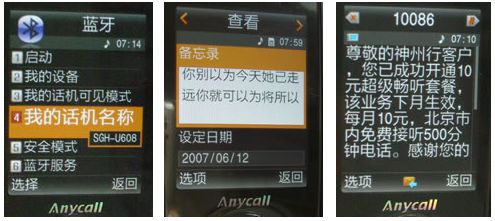
方正字体嵌入解决方案
方案介绍
随着现代电子与信息技术的不断发展,信息处理产品的种类越来越多。常 见的涉及信息处理的软件产品和嵌入式系统包括:桌面操作系统(Windows、Mac、Linux、Unix等)、具有文字处理功能的软件(Office、CAD、OA等)、打印输出设备(Printer) 、手机(Mobile Phone)、电子书(eBook)、电子字典、机顶盒(Set top box)、导航仪(Navigator、GPS)、数字电视系统(Digital TV)、车载娱乐终端(Car dvd entertainment system)、医疗系统、工业控制系统等。为了便于人机交流,多数信息处理产品都配有显示装置。文字是显示装置上最重要的信息!方正作为最资深的中文字体专 业开发商,长期为信息处理软件及嵌入式系统提供完整的用字解决方案。针对液晶显示屏的显示特点,方正公司专门设计并开发了更加易于阅读、清晰美观、实用性强的字体。同 时,为尽可能少的占用嵌入式系统的存储空间,方正还专门开发了采用笔划压缩技术的字库产品,可节约超过75%的存储空间。
以下是方正字体的相关资料,供信息处理软件及嵌入式系统技术开发者参考:
一、方正支持的常用编码标准
1、GB编码:中国大陆使用的国家标准,其中GB2312-80、GBK、GB18030- 2000比较常用;
2、BIG5编码:港台及海外华人常用的标准。香港地区由于方言用字较多,而且与内地交流较多,所以在BIG5的基础上又增补的几千个“香港字”,简称 :HKSCS。目前最新的版本是HKSCS-2008。定义字符5009字;
3、JIS编码:日本国的国家标准;
4、KSC编码:韩国的国家标准;
5、欧洲语系编码:可以支持:英语English、德语Germany、波兰Polish、匈牙利Hungarian、葡萄牙Portuguese、捷克Czech、意大利Italian、西班牙 Spanish、法语French、荷兰Dutch、芬兰Finnish、希腊Greek、土耳其Turkish、瑞典Swedish、俄文Russian等多国语系;
6、Unicode编码:Unicode是国际组织制定的可以容纳世界上所有文字和符号的字符编码方案。方正公司提供的字库完全支持Unicode编码方式;
7、其它语系编码:方正公司可以根据用户的需求定制提供支持其它语系编码方式的字库。
二、常用的字库格式
目前,字库常用的种类有点阵字库和TTF字库(所谓“矢量字库”)。
点阵字库(Bitmap font、Dot matrix font)适合精度很低的显示设备。常用的格式主要有“DAT”、“BDF”、“FNT”、“PCF”、“BMP”等。
TTF字库(TrueType)适合较高精度的显示设备。由于TTF字库是通用、标准的字库。因此,只要是带有TTF解释器的系统都可以直接使用。如:Windows 系统、Symbian系统、Android系统、Unix系统及其它Liunx系统等。
三、推荐的字体种类(应用效果图)
点阵字库:方正公司可以提供支持GB(中国大陆标准)、JIS(日本标准)、KSC(韩国标准)和欧洲语系标准的各种尺寸点阵字库。
TTF字库:针对屏幕显示的特殊性,方正公司专门开发了采用标准TTF压缩格式的黑体、宋体风格的字体。
以下是方正推荐的屏幕用黑体、楷体和宋体的普通字体的对比样例
方正屏幕用黑体与普通黑体的对比效果
注:带有*的为方正屏幕黑体
方正屏幕用宋体与普通宋体的对比效果
注:带有*的为方正屏幕宋体
方正屏幕用楷体与普通楷体的对比效果
注:带有*的为方正屏幕楷体
五、常见问题:
3、关于Unicode的问题
许多主权国家都制定了本国的编码标准,这些编码也叫地区编码,如GB(中国标准)、BIG5(港台标准)、JIS(日本标准) 。Unicode是国家上通用而统一的编码体系。任何一个地区编码与Unicode编码之间都有一一对应的关系。字体厂商提供的字库通常以Unicode编码方式提供,字符集支持地区编码。 地区编码与Unicode编码之间的转换由操作系统完成。
4、使用Unicode编码字库是否可以同时满足中、日、韩市场?
Unicode编码字库可以同时支持中、日、韩三地,但由于文化的差异,许多同一个编码的汉字的写法却不一样。因此,完美的 解决方案是分别使用三个字库支持中、日、韩三国市场的产品。以下是中国大陆与台湾字形的对比:
6、用工具从TTF字库中生成的点阵字库是否可以使用?
网站上有许多“点阵字库生成工具”。这些工具的主要作用就是用TTF字库生成任意尺寸的点阵字库。
点阵字库是TTF字库的一部分。许多TTF字库为了使小字是显示清晰,都内嵌了点阵字库。所以未经字库版权人授权从TTF字库 中生成点阵字库在产品中使用的行为实际上是盗版行为。
典型应用
体会清晰阅读的快感,提高传情达意的效率
——方正压缩字库在三星手机中的运用
三星公司最新推出的 “SGH-U608”手机,以其纤薄,精致,高雅的形象给人留下深刻印象。其中她的字体显示,以独特的风格让人体会到其秀外慧中,别具一格,给人带来全新的使用体验。
从上图可以看出,U608使用的字体字面大,笔划均匀,美观,时尚,给使用者带来清新,爽朗,便于阅读的感觉,特别是把U608和其他手机放在一起,这种感觉会更明显。
U608字体名为“方正兰亭细黑”压缩字库,系出名门,其前身是微软公司最新的Windows操作系统Vista界面使用的黑体字库。他们均是由北京北大方正电子有限公司设计开发。在Vista中使用的字体被命名为“微软雅黑”。甫一推出,用户对“微软雅黑”字体好评如潮。正是在此基础上,方正为U608专门推出了比“微软雅黑”细一档的“方正兰亭细黑”压缩字库。这一款字体具有诸多的优点,其采用的标准TrueType格式和笔划压缩技术两大技术尤其引人瞩目:
标准TrueType格式:“方正兰亭细黑”压缩字库采用标准TrueType格式,压缩字库是专为小型高级数字终端产品而设计的。由于受显示屏精度的限制,以往的嵌入式系统使用的汉字多以点阵字为主。因为显示精度低,所以点阵字库对一些笔画复杂的字做了减笔处理,每个点阵字符必须由人工修改。在字符点阵数小于16x16时,点阵字的显示效果比高精度的曲线字要好。但反之,点阵字的效果则会变差。随着显示屏技术的发展,显示精度越来越高,点阵字的劣势愈加明显。以三星U608为例,该款机型使用的是QVGA彩屏,26万色,TFT,240×320像素,2.2英寸。同样是12磅大小的字,30X30点表示的QVGA的显示屏与16X16点表示的传统显示屏相比,大大提升了对字体的表现力!
笔划压缩技术:在保证精度的同时,降低存贮空间的占用也非常重要。为了最大限度减少存贮量,方正电子设计的“方正兰亭细黑”压缩字库采用了笔划压缩技术。这一技术的采用,使得支持GB13000标准的20484个汉字的字库仅占用不到2M的存贮空间。这给嵌入式系统节省了至少6M的空间。
随着技术的发展,屏显精度越来越高,嵌入式操作系统日臻完善,小型数字设备的处理速度也越来越快。这一切都为使用高质量字库提供了有利的条件。“方正兰亭细黑” 压缩字库已成为高档小型数字设备的最佳选择!这款压缩字库让使用者可以更好的体会清晰阅读的快感,提高传情达意的效率。